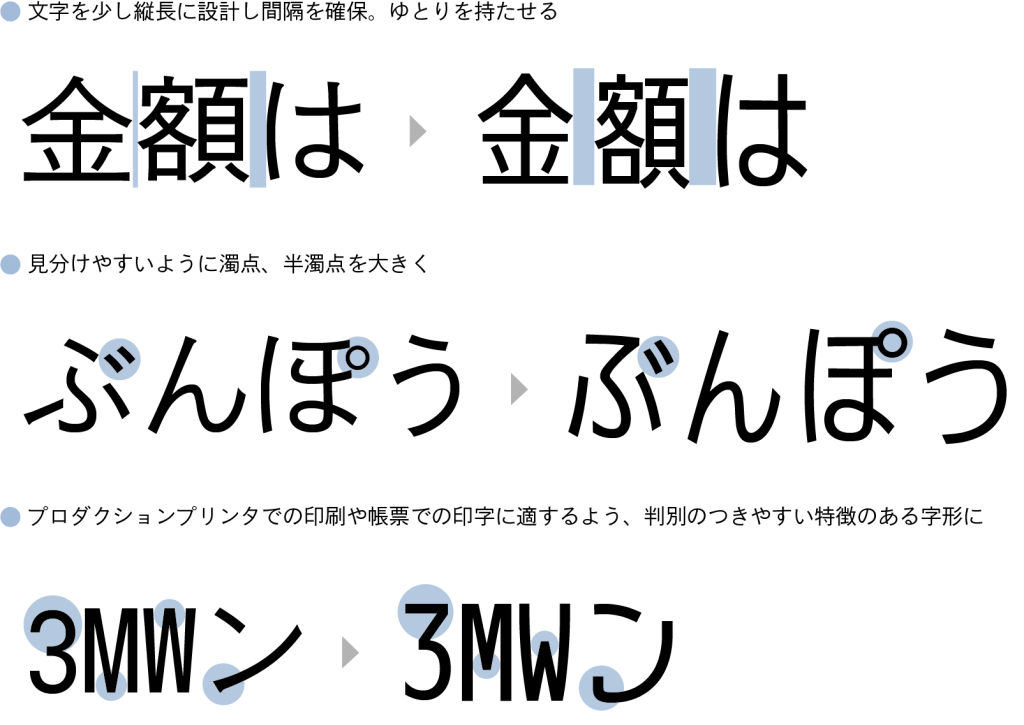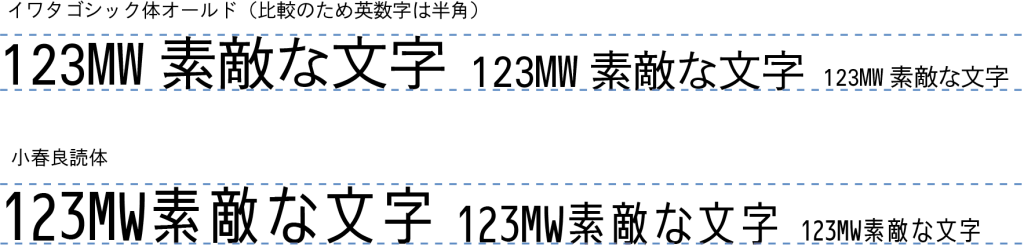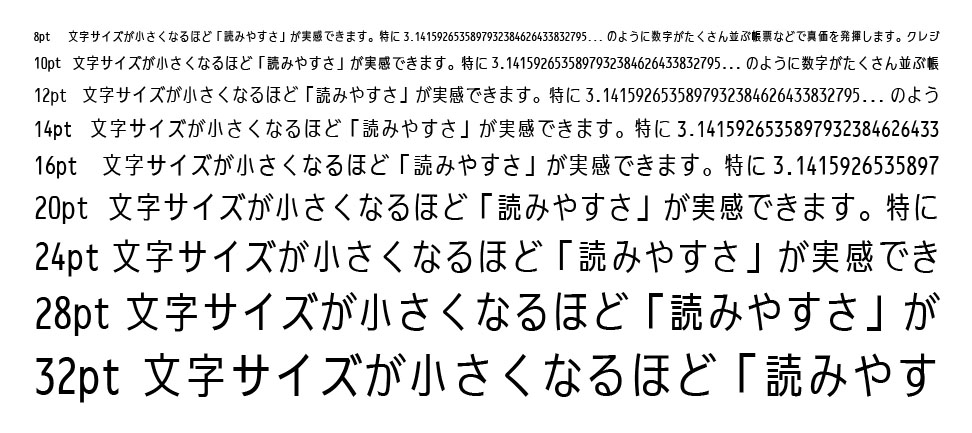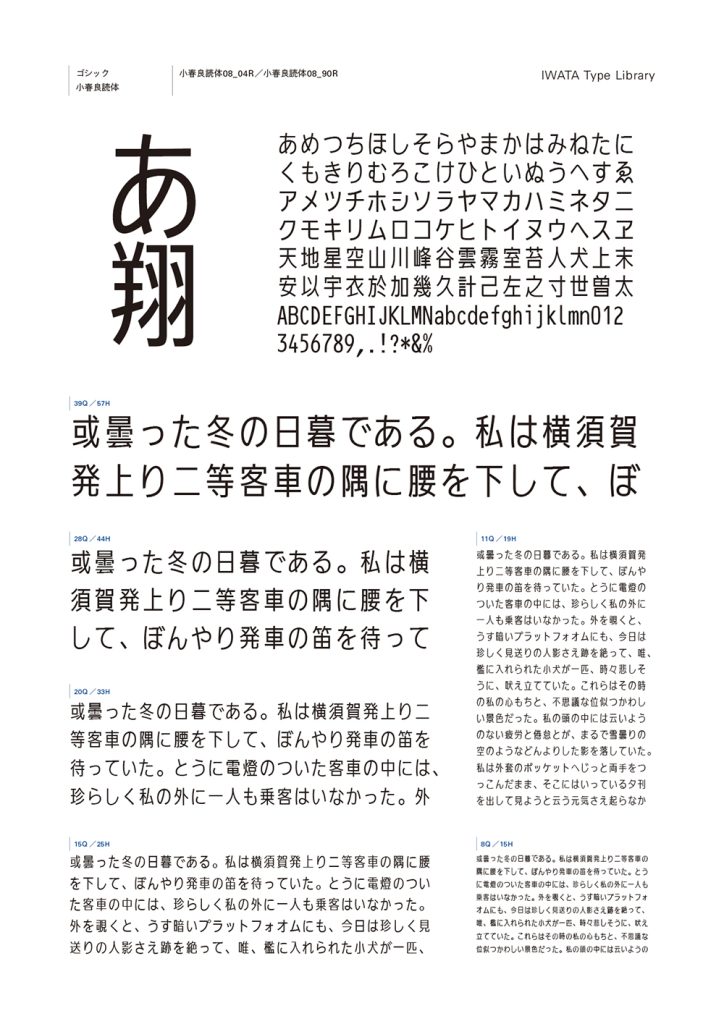
共同印刷株式会社と、東京女子大学の小田浩一教授の共同研究により生まれた、横組み用のユニバーサルデザイン(UD)ゴシック体です。UD フォントの知見豊かなイワタが、漢字の拡張をはじめ制作に全面協力しました。とくにプロダクションプリンタでの印字に適しており、帳票、通知文書、契約書、証明書などの小さな文字に効果的です。通知物などの印字処理はもちろん、一般印刷物や組込みにも幅広くご利用いただけます。
書体デザインのポイント
文字を少し縦長に設計することで横の文字との間隔を十分に確保、それでいてしっかり大きく見えます。さらに濁点などの細部を大きくしたり英数字を見分けやすい形状に調整することで、優れた視認性・判読性を実現した汎用性の高い書体です。
※「イワタゴシック体オールド」と「小春良読体」を比較しています
同じサイズでも大きく見えて読みやすいのが特徴です。文字サイズが小さくなるほど読みやすさを実感することができます。
「小春良読体」は、MNREAD-J※で読みやすさの検証を行った結果、通知文書などで一般的に使用されているゴシック体と比較して、より読みやすいと評価されました。
※MNREAD-J(エムエヌリード ジェイ)…………ミネソタ大学ロービジョン研究室が開発した読書視機能検査「MNREAD」の日本語版で、同研究室と東京女子大学・小田研究室により、日本人の読書行動やニーズを踏まえて開発されたものです。評価項目には、①読書視力(読書が可能な最小文字サイズ)、②最大読書速度(標準的な読書速度)、③臨界文字サイズ(最大読書速度を維持できる最小文字サイズ)などが含まれます。